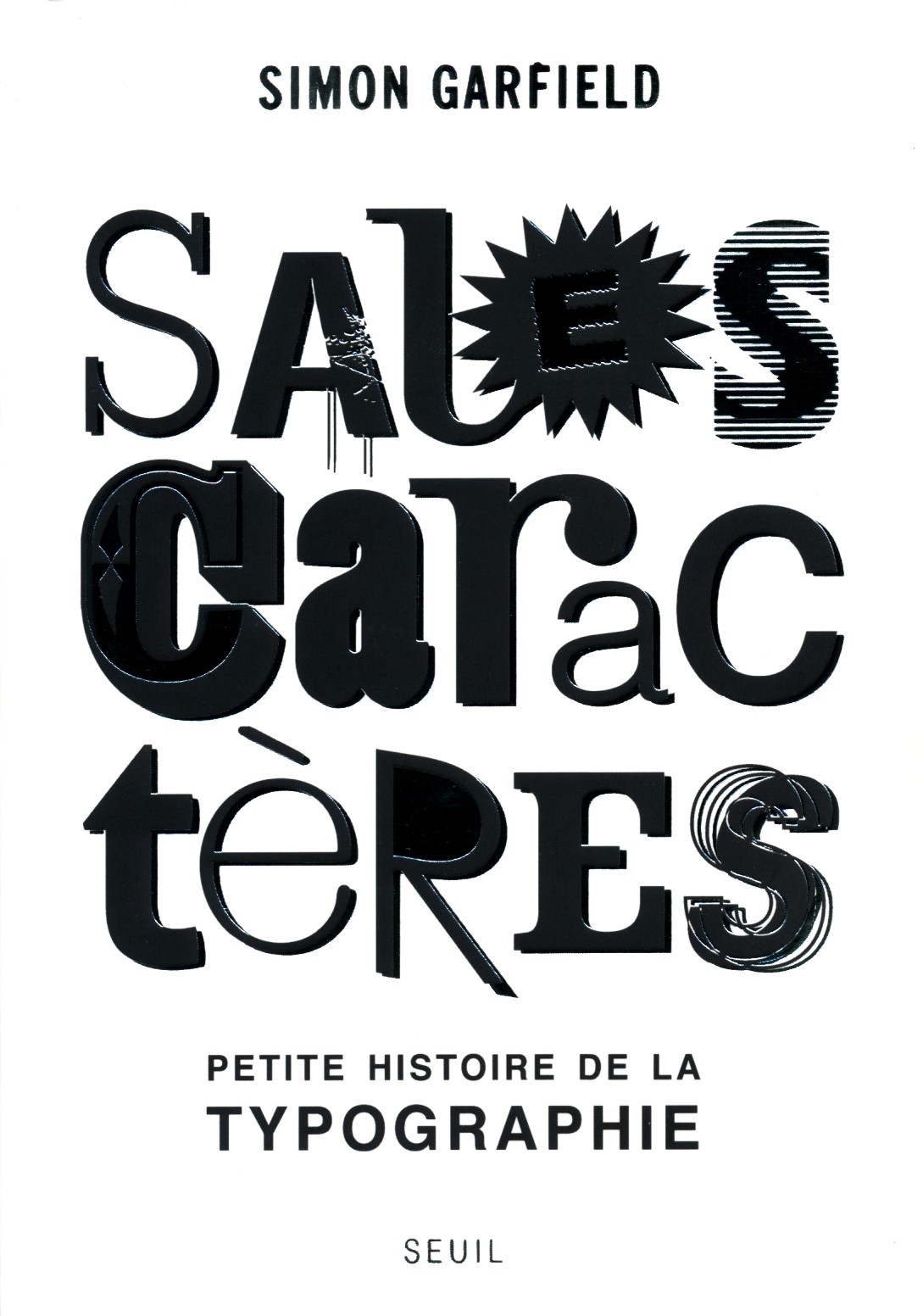
SALES CARACTERES - PETITE HISTOIRE DE LA TYPOGRAPHIE
Times New Roman, Garamond, Arial, Courier, Verdana... La fréquentation quotidienne de l'ordinateur a popularisé le nom et l'usage des polices de caractères. Mais que savons-nous de ces fameuses fontes, comme les appelaient autrefois les imprimeurs ? Rien ou pas grand-chose...
Simon Garfield entreprend de nous raconter l'histoire de quelques-unes des 100 000 polices de caractères créées depuis l'invention de l'imprimerie. Car derrière chacune d'entre elles se cache un destin, drôle et parfois tragique, qui croise souvent la grande Histoire ? L'auteur raconte ainsi comment la police Gotham contribua à l'élection de Barack Obama.
Les polices de caractères constituent aujourd'hui l'une des dimensions centrales de notre culture visuelle dont nous n'avons en général pas conscience. Qui sait que l'Helvetica a colonisé la signalétique urbaine outre-Atlantique et qu'elle est utilisée par toutes les grandes marques commerciales pour sa moderne efficacité ?
Simon Garfield est journaliste indépendant et auteur de nombreux livres.